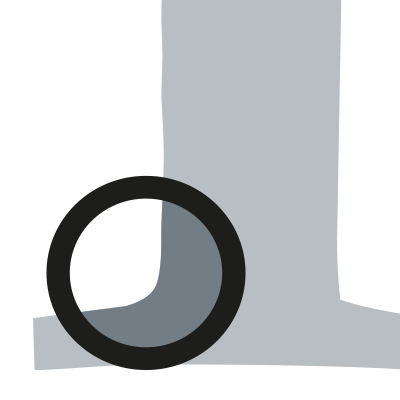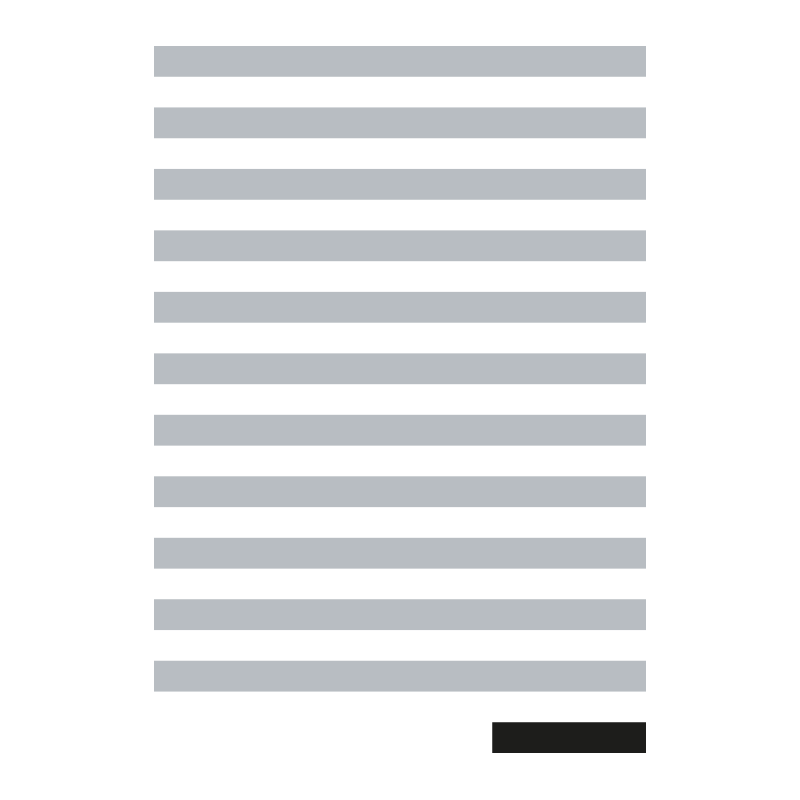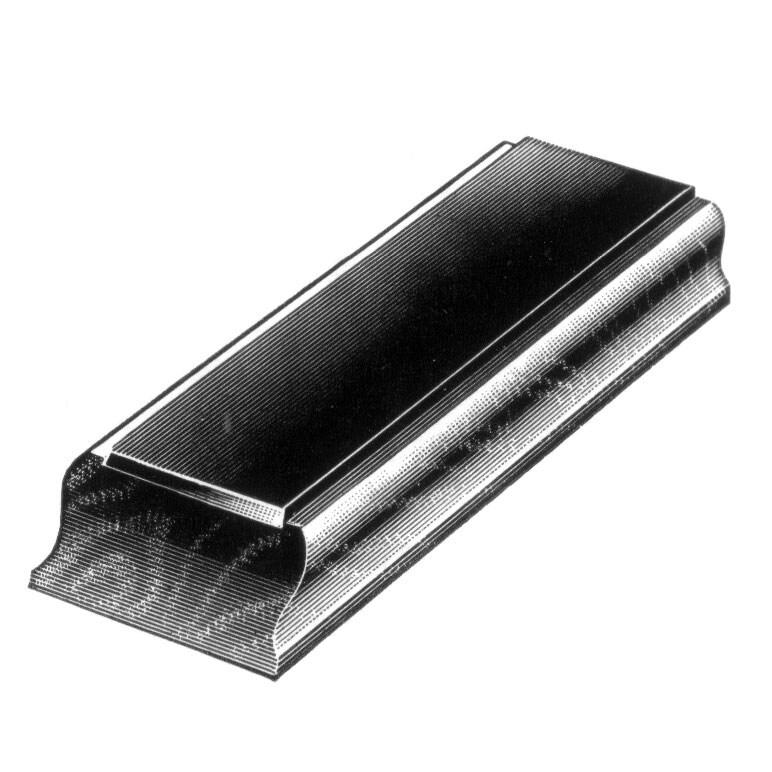
Kalligrafie (griechisch καλλιγραφία kalligraphía, von καλός kalós, deutsch ‚schön‘, und -grafie) bezeichnet die Kunst des »Schönschreibens«. Die Kalligrafie grenzt sich dabei eindeutig von der Typografie ab, bei der die Buchstaben aus Einzelbuchstaben »gesetzt« statt geschrieben werden.
Das Kapitalband (oder kurz »Kapital«) ist ein kleines, oft farbig abgesetztes Bändchen, das bei Hardcover-Büchern und Deckenbänden an der Ober- und Unterkante des Buchrückens angeklebt ist. Es kann die Stabilität des Buches verbessern, dient aber in jüngerer Zeit vor allem der Dekoration.
Kapitälchen (englisch Small Caps) sind formal-gestalterisch Großbuchstaben, die aber in etwa in der Höhe der Kleinbuchstaben, also der x-Höhe der Schrift, gezeichnet sind. Im Kapitälchensatz werden Versalien und Kapitälchen so kombiniert, dass die Kapitälchen jeweils an die Stelle treten, wo sonst im gemischten Satz Kleinbuchstaben benutzt worden wären. Man hat es also gestalterisch mit reinem Großbuchstabensatz zu tun, der aber gleichsam durch die unterschiedlichen Größen die in der
Alternative Bezeichnung des Et-Zeichens.
Die Kegelhöhe beschreibt den Raum, auf dem der gesamte Buchstabe sitzt. Die Bezeichnung geht auf den früher gegossenen Bleisatz-Kegel zurück, der das Buchstabenbild trug. In digitalen Schriften können die Buchstabenteile heute auch über den Kegel hinausragen. So liegen die Akzente von Großbuchstaben oft teilweise oder gänzlich außerhalb der eigentlichen Kegelhöhe. Die Kegelhöhe ist identisch mit der Angabe der Schriftgröße.
Eine (Hohl-)Kehle ist eine konkave Einbuchtung an einer Kante. In der Typografie wird der Begriff Kehlung insbesondere zur Beschreibung entsprechend angesetzter Serifen verwendet.
Klischee (von französisch cliché) ist die Bezeichnung für die Nachbildung eines Originals in irgendeinem Produkt (Holz, Kupfer, Messing, Zink usw.), die geeignet ist, in der Buchdruckpresse gedruckt zu werden; auch Stereotypabgüsse, galvanische Reproduktionen, Holzschnitte und Ätzungen mit bildlichen Darstellungen sowie Schriftsatz-Reproduktionen werden so bezeichnet.
Das Klopfholz ist ein Werkzeug beim Buchdruck. Das Klopfholz besteht – wie der Name schon sagt – aus einem Stück Holz, das meist an der Oberseite mit einem leicht elastischen Material wie Leder oder Linoleum bezogen ist. Mit dem Klopfholz werden die druckenden Elemente (insbesondere die Lettern) der Druckform auf der Schließplatte »verklopft«. Dadurch wird sichergestellt, dass in der Form keine Elemente über die Schrifthöhe hinaus hochstehen. Die Schläge auf das Klopfholz erfolgen mit einem leic
Eine Schnur, mit der Satzspalten oder gesetzte Seiten durch mehrfaches Umwickeln zusammengehalten werden. Der Prozess wird Ausbinden genannt und dient dem einfacherer Transport oder zur Lagerung als Stehsatz.
Im Bleisatz bezeichnet kompress Schriftsatz, der gänzlich ohne Durchschuss angelegt ist. In digitalen Textverarbeitungen beschreibt kompress dagegen heute das Weglassen von Leerräumen, zum Beispiel vor oder nach Interpunktionszeichen.
OpenType-Fonts bieten zahlreiche, erweiterte typografische Funktionen. Dazu zählen auch kontextsensitive Ersetzungen (englisch: contextual alternates). Eine reguläre Ersetzung wäre zum Beispiel das Ersetzen jeder auftretenden Buchstabenkombination f i mit der entsprechenden fi-Ligatur. Eine kontextsensitive Ersetzung hingegen macht die Ersetzungen von dem Kontext abhängig, in dem die gesuchte Zeichenkette auftritt. So könnte zum Beispiel geprüft werden, ob die Buchstabenkombination f i am A
Der Begriff Kurrent kann im weitesten Sinne als Synonym von Schreibschriften (von lateinisch currere: »laufen«) benutzt werden. Diese Bedeutung ist jedoch nicht die übliche. In der Regel meint man mit Kurrent einen spezifischen Schreibschriftstil des lateinischen Schriftsystems, der auf die gotische Kursive des 15. Jahrhunderts zurückgeht und sich im deutschsprachigen Raum bis ins 20. Jahrhunderts als verkehrsübliche Schreibschrift halten konnte. Die Kurrent bildet als Schreibschrift das Pendant
Als Kursive bezeichnet man Schriftschnitte, die im Gegensatz zum aufrechten Normalschnitt (englisch: »regular« oder »roman«) schräg laufen (englisch: italic). Die kursive Schrift geht auf die Handschrift zurück und behauptete sich lange Zeit als eigenständige Schriftform neben den frühen Monumental- und späteren Druckschriften. Die Bezeichnung »kursiv« geht auf das lateinische »currere« (laufen) zurück und spiegelt die fließenden, verbundenen Formen einer (oft eher flüchtig geschriebenen) Hand